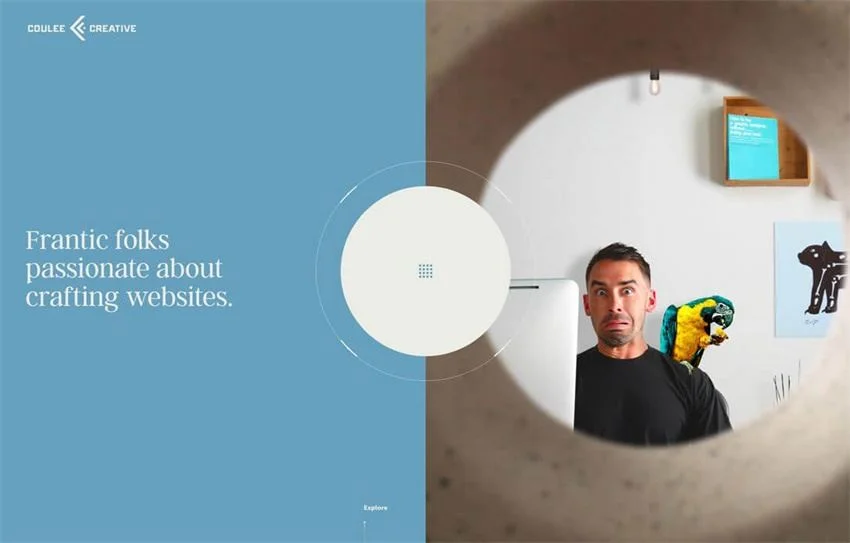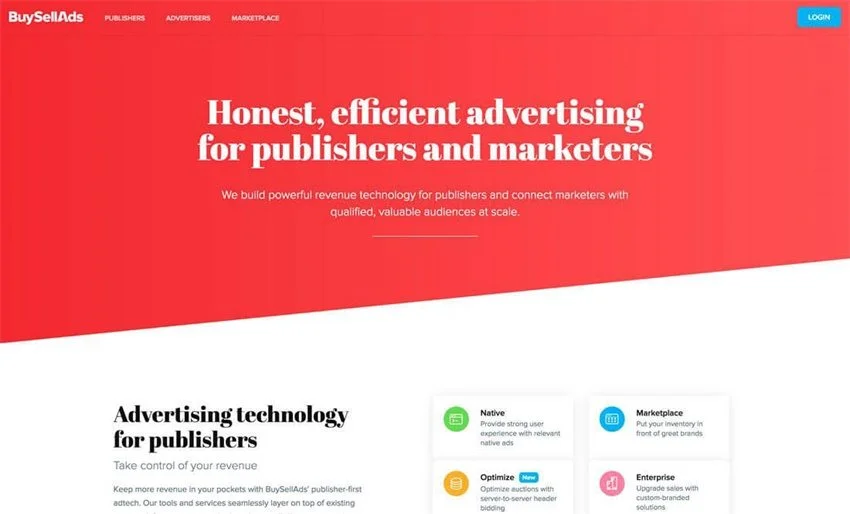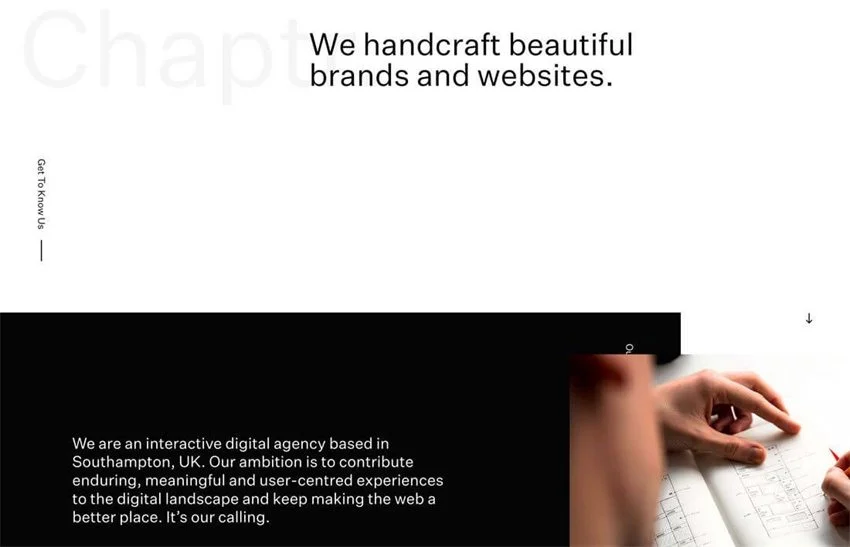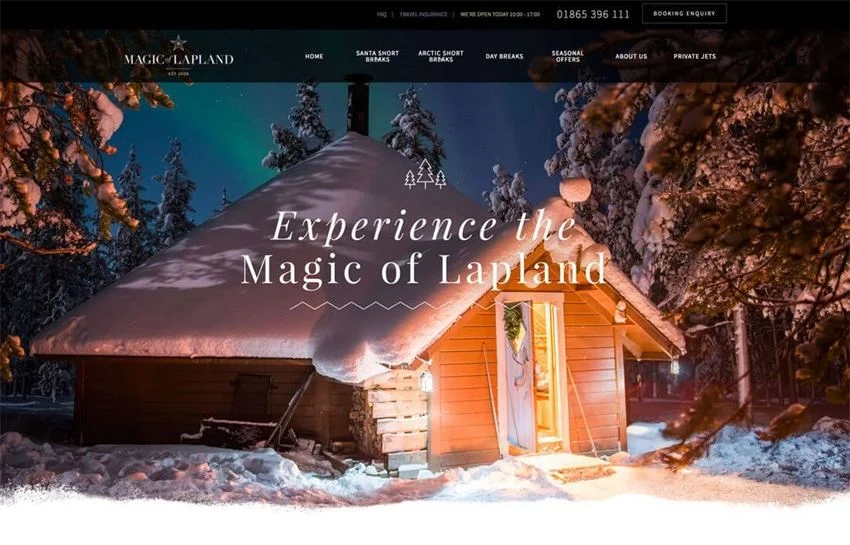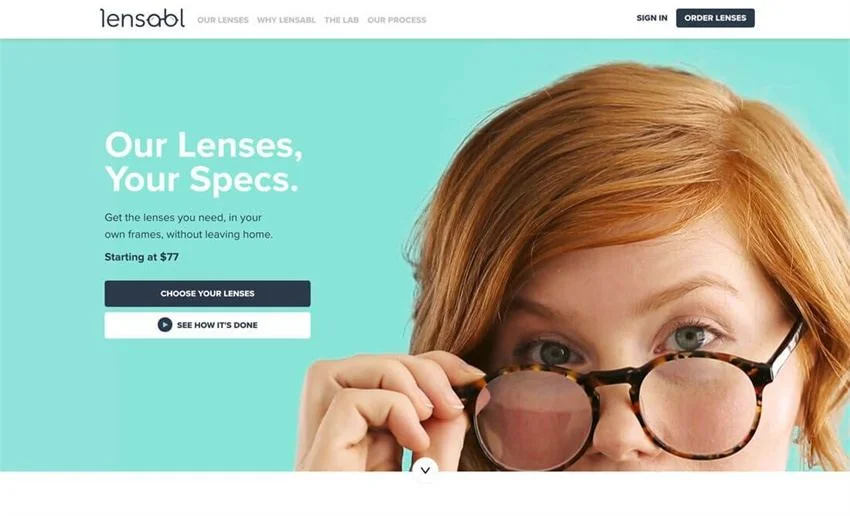
@喪心病狂十六夜貓 :對於設計師而言,為每個項目選擇合適的字體,是已經掌握的特殊技能。今天這篇文章可以讓你通過應用一些簡單的規則,就能設計出適用於電子、印刷技術或提升項目檔次的字體。
如果你正在為選擇字體組合而感到困惑,遵循本文規則,你就可以設計出優秀的字體。
1. 定位項目重點
項目開始時,我們需要明確設計目的。當你在Google Font或Typekit等網站尋找字體之前,先問問自己以下幾個問題:
項目面向的目標人群是什麼
用戶會怎樣對待這個設計
適合怎樣的氛圍、心情
需要和其他的設計、品牌相匹配嗎
這些答案將幫助你構建出設計的初步框架。
2. 找到相同屬性的字體
設計許多的字體組合時,字體的形狀細節會影響設計的的好壞。那麼,你應該如何進行正確的選擇?
首先尋找相似形狀的字體。讓我們仔細研究每種字體是圓形還是橢圓形、粗或細、高或短、對角的還是傾斜的。
選擇要用於標題和正文的字體後,將同樣形狀的輔助性字體組合在一起。
確認一下各種字體的小寫「o」。內側是圓形還是橢圓形?將[o]形狀相同的字體組合在一起。
選擇x字高(英文:x-height)相同的字體。
不用擔心混合字體風格。襯線和無襯線字體的組合也可以嘗試。如果選擇了一格複雜的字體,另一種字體選擇簡單點的會比較好。此外,使用最頻繁的地方,如正文,我們還是選擇一個簡單的字體方便閱讀。
小心字體的傾斜度。使用多個斜體或相反方向傾斜的字體對可能會給用戶的閱讀帶來不適,應該避免。
3. 設置同類型字體尺寸
字體的粗細,尺寸是決定項目的好壞的因素之一。文字的尺寸過大會讓視線停止,讓人無法自然的閱讀。另外,文字尺寸過小則會導致視覺疲勞,用戶或許會從設計作品上移開視線。
通過正確的設定字符大小,用戶可以在內容上自由的閱讀。合適的文字尺寸是:和項目中各種各樣的尺寸相對應。
正文內容、小標題或大標題等有著各種各樣的尺寸。這些尺寸和使用方法,必須保證在設計內具有一致性。
注意以下幾點,用戶會更容易閱讀內容。
文字內容的尺寸,可以根據信息的重要程度來確定優先順序。字體越大內容越重要,佔用用戶視覺範圍的可能性就更高。
通過縮小文字的尺寸,可以讓文本閱讀速度更快,能讓用戶用更短的時間確認內容。
較大的文本元素,可以通過分割長句來更使其容易閱讀。
4. 設置留白空間
這種方法本身與字體無關,但是在選擇字體時,設置留白的方式也很重要。
字距、行距、跟蹤、填襯這些方法,能表現出字體的美感,也有可能將他們弄的亂七八糟。
適當運用留白,會讓你設計稿更精緻。但它還取決於在實際項目中使用的字符、字體等的組合和大小。
5. 選擇左對齊
和其他語言一樣,用戶在閱讀英語、日語、中文的時候,都是從左往右移動視線的,所以理想的突出主體內容可讀性的方法是左對齊。
如導航標題和Hero Header,一些文本本身就很容易閱讀,所以不用將它們對齊到左邊。而對於長句子來說,應該將它們對齊到左邊。
6. 選擇兩種字體
在設計項目中使用了兩個字體,這個規則可能很多人知道。
當你打破這個規則的時候,可以看看是否可以用該字體的另一種樣式:如粗體、細體、斜體來解決。
7. 不要修改默認的字型
不要去伸展,扭曲,或傾斜你的字體。如果您需要不同的字體,請嘗試選擇其他方法。
字體設計師花費了大量的時間來做一款好看的字體。如果更改字型,將會損害字體的可讀性。
8. 使用大量的對比
設計師很困擾的一個問題是:如何在圖片或背景上加文字。
當給文字添加陰影時,不一定會獲得足夠高的對比。通過調整亮度,可實現輕鬆對比,也有助於將普通的風格變得厚重。
有些情況下,照片中既有亮也有暗的地方的情況下,你就可以利用粗體字或細體字形成對比。
讓我們考慮選擇附加文本,選擇較厚的字體,並嘗試在照片上疊加顏色。所有的技術都是為了突出了對比,使文本更具可讀性。
9. 不要忘記移動端的排版
關於網站排版的問題,移動終端的可讀性是最重要的一個問題。雖然給文字添加圖案或紋理在某些桌面屏幕上進行打印或顯示時不會出現問題,但對於小型設備來說效果並不理想。
所以,考慮這個字體適用在什麼地方是很重要的。
對於移動終端來說,字體看起來會略大一些,所以讓我們把字體間距做得比桌面寬一點。通過這樣做,可以有效減少用戶不喜歡的移動操作,例如在閱讀短句時多次滾動顯示。
10. 參考風格指南
當您決定要用某種字體在項目時,你需要一個總結了所有用法和規則的樣式指南。
比如:請你的元素移至在網頁上易於訪問的位置,並在該位置修改你的設計。
所以,完美的字體設計的關鍵因素是:統一性。
總結
字體的好壞,應由用戶來決定。
為了設計出完美的排版,利於閱讀是最重要的一點。字體容易閱讀,便容易理解。所以,為了達到用戶可以隨時閱讀而不用考慮任何事情的目的,字體也應該符合場景想要傳達的信息和氛圍。